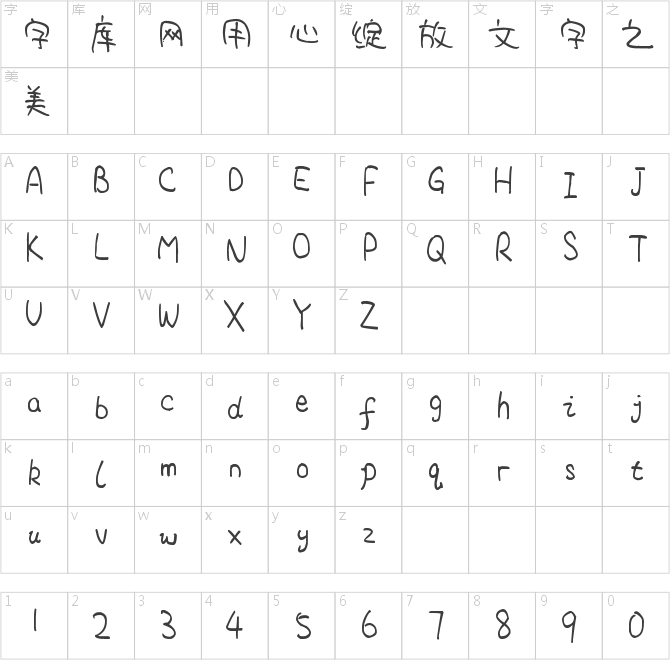
米開一世風(fēng)華
米開一世風(fēng)華字體米開一世風(fēng)華體字庫(kù)是一款讓人賞心悅目、百看不厭的中文字體,適合各類廣告和產(chǎn)品包裝設(shè)計(jì)應(yīng)用,字體大小2.46MB,格式為TTF字體,上傳用戶是金百誠(chéng),作者/版權(quán)方為米開字庫(kù)